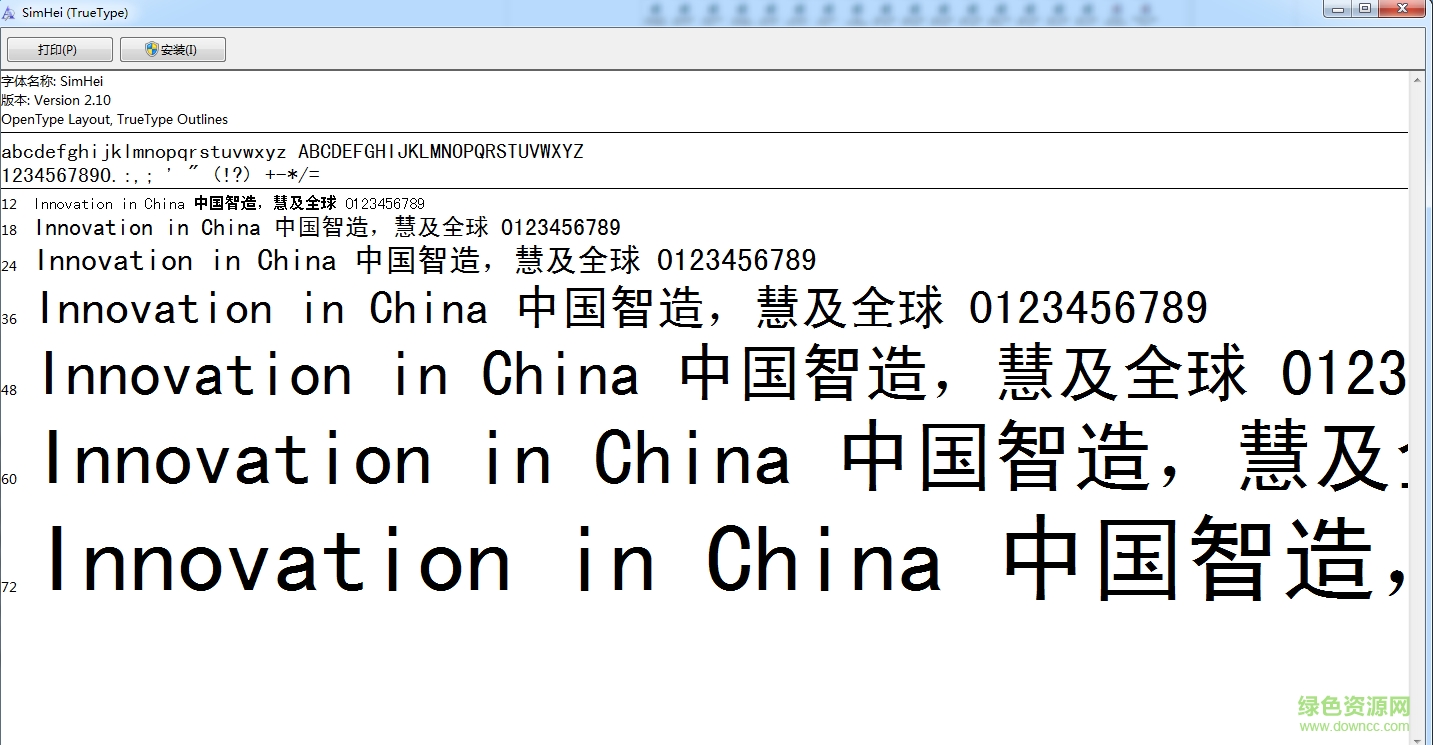
開票系統(tǒng)黑體字體是一款常常用于電腦開票軟件的黑體字體,該字體線條粗細(xì)相當(dāng),結(jié)構(gòu)端正,印刷效果清晰明快,整體莊重大方,有需要者歡迎在綠色資源網(wǎng)下載!
開票黑體字體筆畫干凈簡練毫無裝飾,線條流暢自然,字形端正大方,適合用于各種正式書面文件或排版方面!
黑體與白體相反,沒有襯線裝飾,筆劃粗壯有力,撇捺等筆畫不尖,使人易於閱讀。黑體是在現(xiàn)代印刷術(shù)傳入東方後依據(jù)西文無襯線體所創(chuàng)造的。所以黑體這個(gè)詞的范疇和無襯線字體是類似的。而宋體就可以被稱作襯線字體。